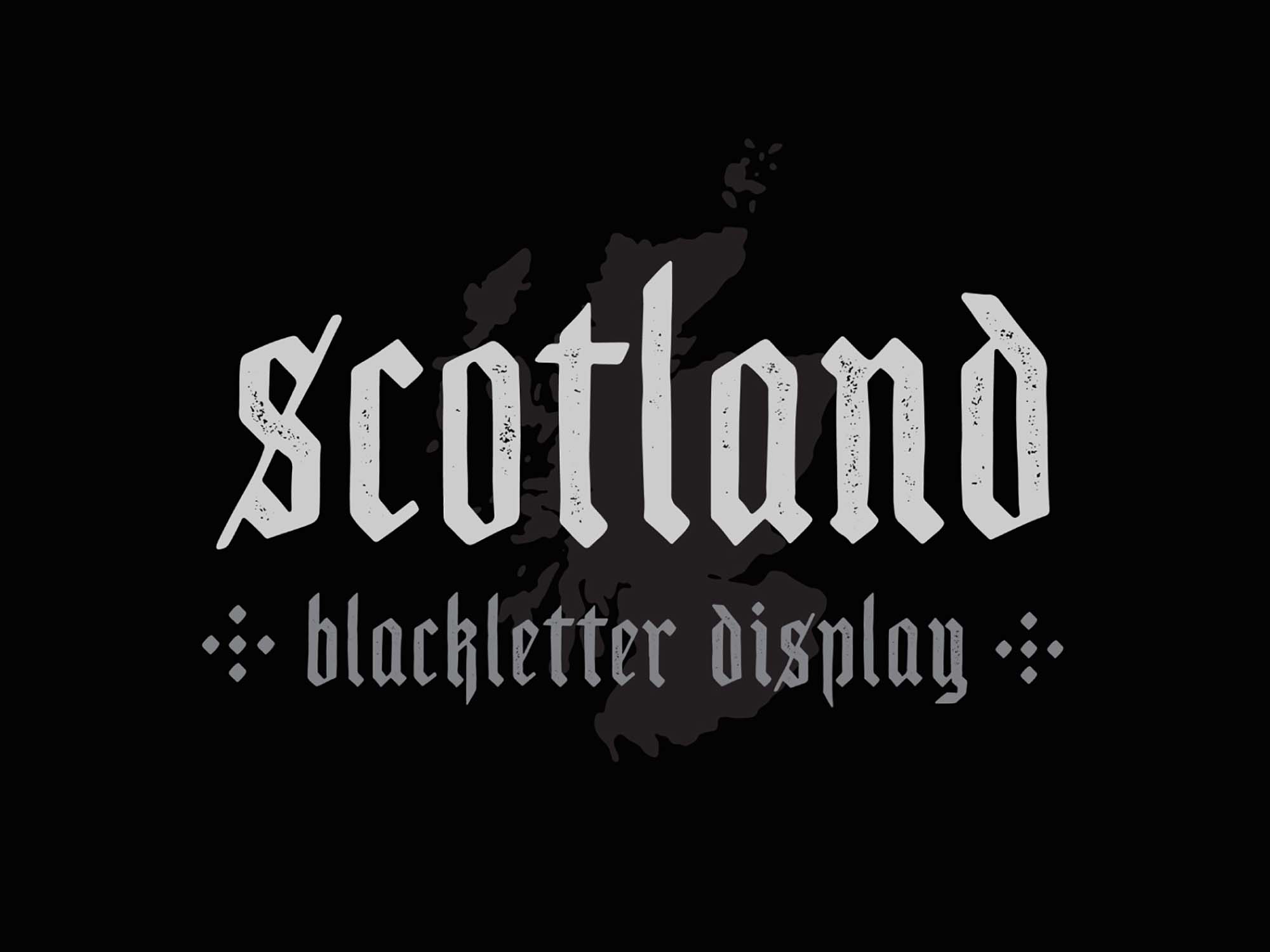
Scotland Blackletter Display Font – Download Grátis
Esta página de download apresenta uma fonte de estilo Blackletter escocês, ideal para designers em busca de inspiração vintage e retro. Inspirado em elementos da cultura escocesa, essa fonte captura a essência arcaica e única da arte gráfica do passado, adaptada para a conveniência e precisão modernas. O design do Blackletter escocês combina a elegância e o encanto que tanto fascinam os criadores, oferecendo uma opção perfeita para qualquer projeto que busca um toque de elegância clássica e personalidade distintiva. Com esta fonte, designers podem criar uma conexão forte com o passado, incorporando a essência de uma era passada em suas criações atuais. Seja para identidades de marca, design de tipo ou até mesmo para sites e aplicativos, esta fonte Blackletter escocesa oferece uma maneira moderna de reviver o encanto do estilo clássico.
Licença: , Scotland is an old-school, blackletter display font which features a subtle vintage texture that has the required effect without being too imposing. Available for both personal and commercial use, the font offers lowercase alphabets that can be used in any kind of traditional, grunge or vintage design projects.